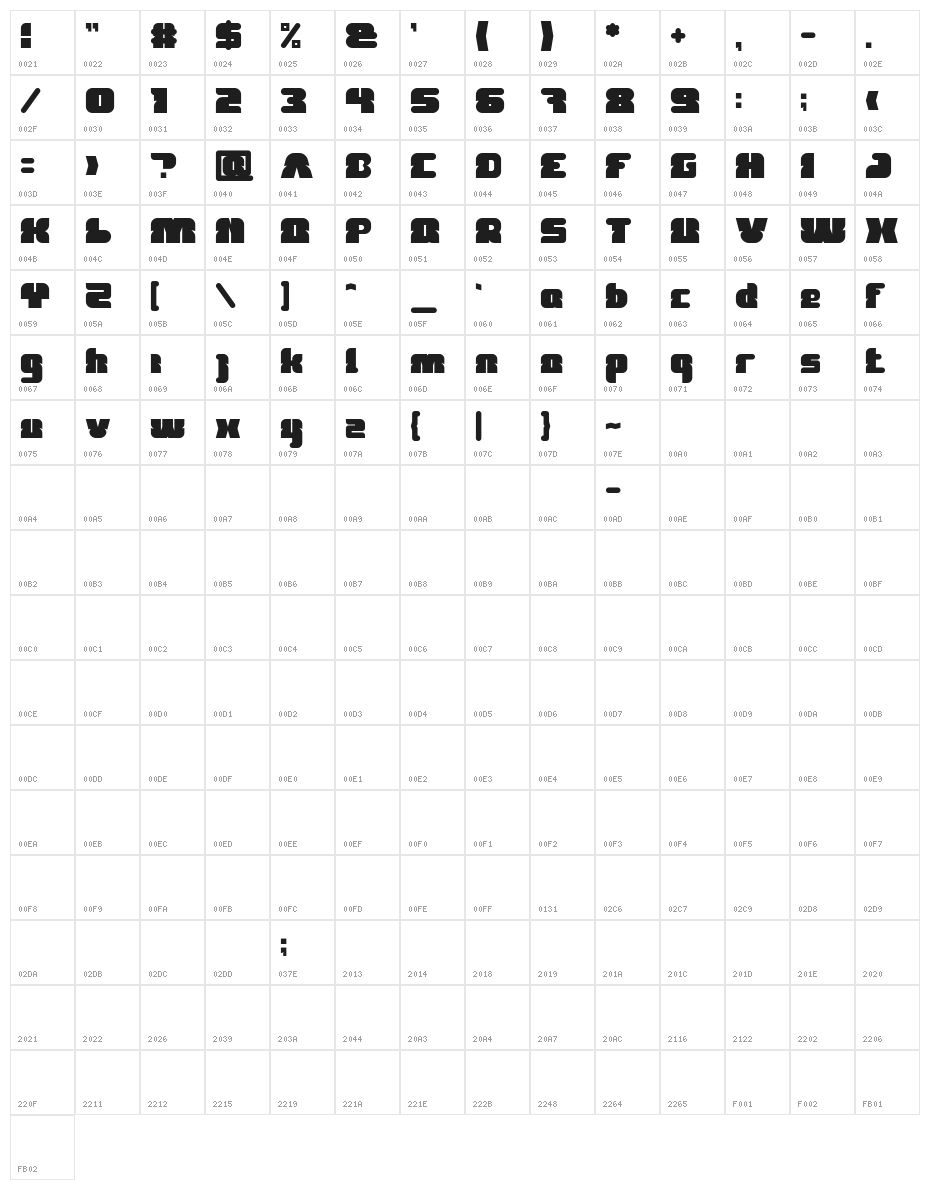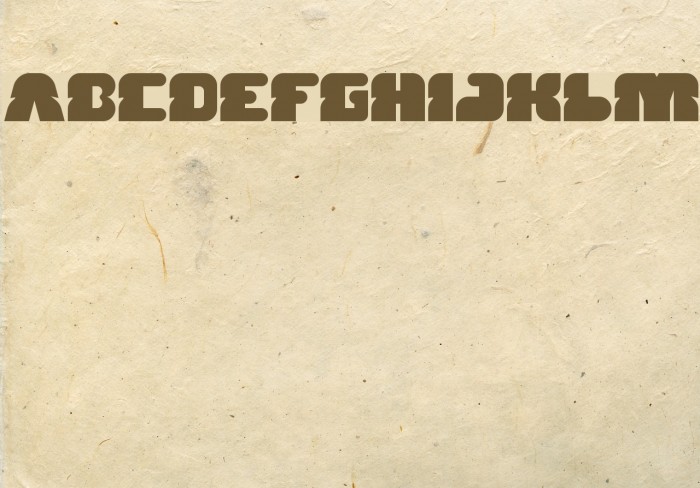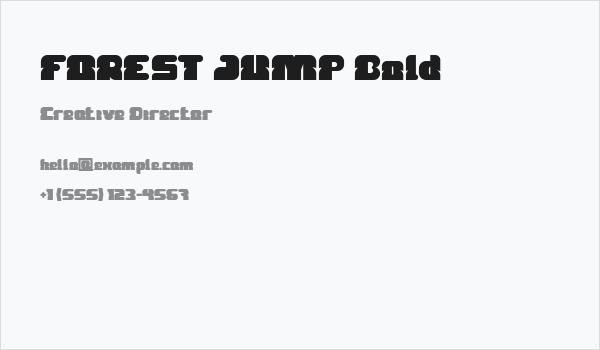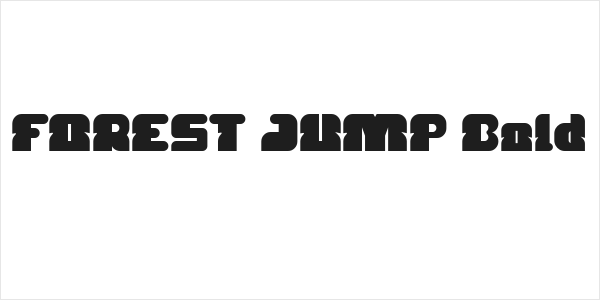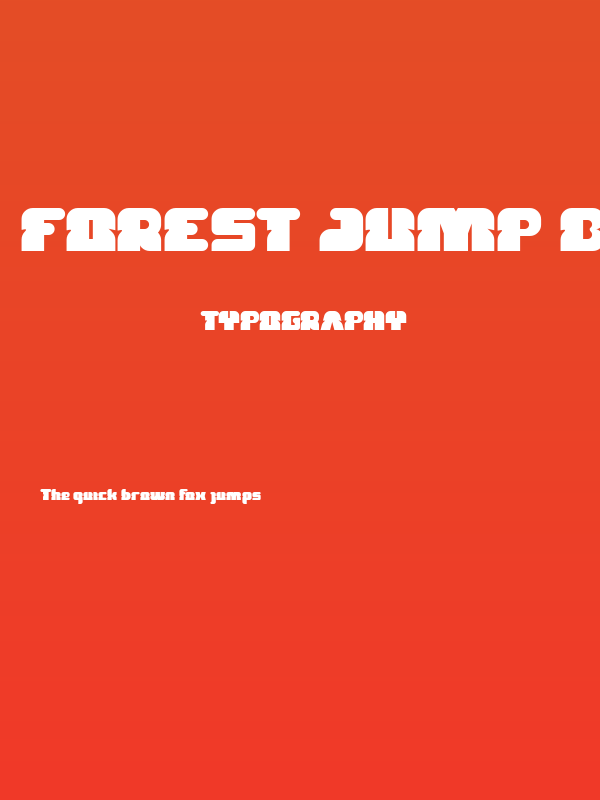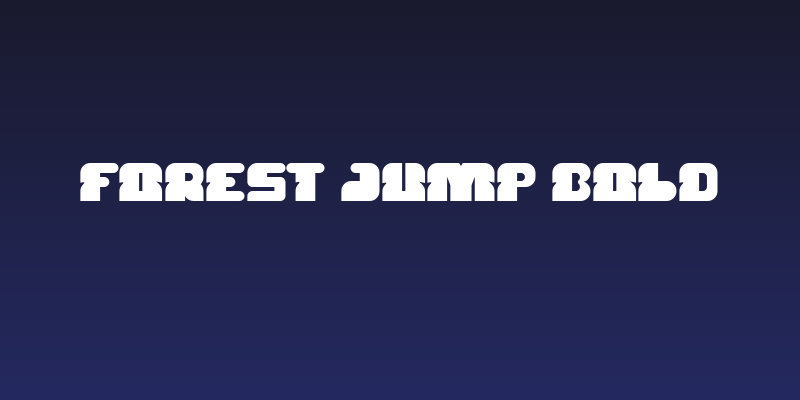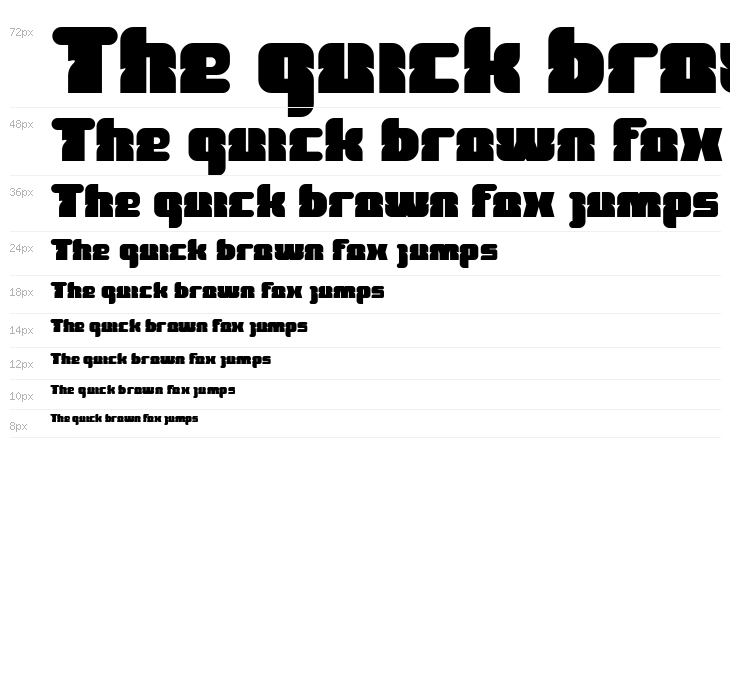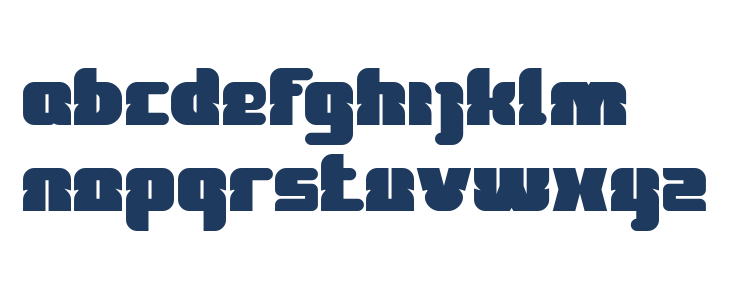
FOREST JUMP Bold Font
✎ Thick
| Vorgeschlagene Projekte | Ideal for posters, headlines, logos, and branding materials where a strong visual impact is desired. |